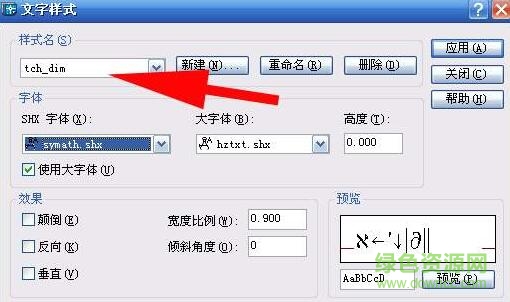
tch_axis字體是天正cad軟件中的TCH軸字體文件。和大多數(shù)cad字體一樣,都是為了方便建筑行業(yè)繪圖工作人員查看圖紙用的。這個字體很難找到,目前無法為大家提供tch axis字體包。先提供下網(wǎng)友們需要迫切搜索的tch axis問題解決辦法!
解決方法:
先選中軸號,用li命名查看軸號字體樣式是什么。查看_TCH_AXIS。然后st,在字體樣式下面找到_TCH_AXIS,修改相應的字體。確定應用就好了。
TCH軸圈里的字體怎么改為txt的?
解決方法:
1)在天正8.5建筑的天正菜單里的設置下拉菜單,選擇“尺寸樣式”,找到要修改的尺寸名稱:選擇“修改”選項,然后找到“文字”分頁欄,里面有文字樣式旁邊的小方框按鈕,(上面有三個省略號)然后彈出文字樣式對話框。將字體中的“shx字體”下面的選擇框中選擇出你所需要的“txt”字體。
2)軸號里面的字體修改,在天正8.5建筑的天正菜單里的設置下拉菜單,選擇“文字樣式”,找到樣式名“_TCH_AXIS”,選擇autocad字體選項,然后將下面的中文字體選為“txt”